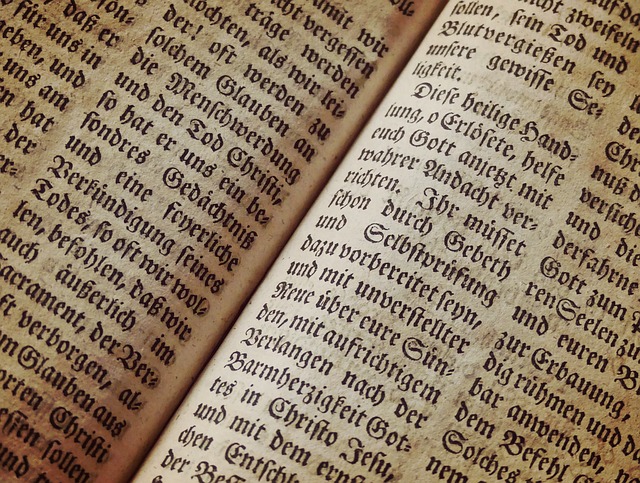
15 règles d’or pour maîtriser la typographie
Dans la construction d’un visuel, le texte est bien souvent indissociable de l’image, même s’il est présent en faible quantité.
Pour des raisons d’équilibre, autant que de puissance de l’image, vous devez consacrer autant de temps à la typographie de ces quelques mots qu’au recadrage et autres effets de filtres retenus.
C’est pourquoi nous vous présentons aujourd’hui 15 règles de typographie à connaître absolument.
1) Connaître les polices de caractère
Chaque police de caractère transmet un message particulier. Une typographie manuscrite n’aura pas le même effet qu’un font plus massif, des mots qui semblent dactylographiés avec une vieille machine à écrire laisseront une impression différente que s’ils paraissent tracés à la craie…
Étudiez les polices, pas seulement pour leur apparence, mais pour ce qu’elles dégagent. Et retenez celles qui correspondront au public et au type de sensation que vous souhaitez communiquer.
2) Limiter le nombre de polices utilisées
La diversité, c’est une très bonne chose. Mais pas pour la conception d’un visuel. Une police de caractère pour le titre, une pour les sous-titres et une troisième pour le contenu, c’est le maximum que vous pouvez vous autoriser.
Ne vous éparpillez pas trop  : les caractères retenus doivent aussi s’associer entre eux.
3) Doser soigneusement la couleur
Méfiez-vous de l’effet arc-en-ciel  : trop de couleurs tuent la couleur. Retenez les couleurs qui ont été sélectionnées pour le visuel et reprenez-les pour les textes.
Ou intégrez dès le départ dans la conception de votre projet la teinte qui sera appliquée aux lignes écrites en respectant toujours cette limite de deux à trois valeurs différentes, au maximum, pour un graphisme.
Soigneur les couleurs pour réussir une typographie
4) Aligner avec précision
Savoir positionner un texte, c’est aussi guider la lecture. Or, dans notre culture, nous avons appris à lire de gauche à droite. Un texte aligné à gauche sera donc nettement plus facile à parcourir.
Respectez le même alignement pour toute la typographie d’un document, sauf à vouloir créer des blocs de texte indépendants les uns des autres.
5) Placer les grands devant, les petits derrière
Quelle que soit la mise en page, l’œil sera en premier attiré par les parties de texte plus grandes, ou d’une couleur différente. Jouez avec les tailles pour capter l’attention des lecteurs.
Il vous faudra sélectionner le mot le plus important, celui qui sera mis en avant. C’est lui qui donnera envie de lire les autres  !
6) Profiter des espaces vides
Le vide, sur un visuel, ce n’est pas le néant, c’est un cadre qui met en valeur ce qui est présenté. Laissez respirer votre texte, ne le collez pas sur les bords de l’image.
Les interlignes, les lignes blanches, sont aussi importants dans la composition de la partie rédigée que le contenu lui-même.
7) Suivre les tendances (ou pas)
Pour trouver l’inspiration, il est bienvenu de regarder ce qui se fait autour de vous et d’en tirer des leçons.
Vous observerez par exemple sur Type Inspire de nombreux exemples de polices ou de mises en page typographiques.
Mais méfiez-vous des modes  : elles peuvent passer très vite et certaines « tendances du jour » seront déjà obsolètes demain. Humez l’air du temps, mais ne cherchez pas absolument à le reproduire s’il ne convient pas à votre projet.
8) Formez-vous
On ne s’invente pas typographe du jour au lendemain. Si vous ne connaissez pas des termes comme « sans serif », ligature ou lettrine, vous n’irez pas très loin dans ce domaine.
Étudiez les différents types de typographie, passez quelques jours à apprendre un mini-glossaire et à voir ce qui se crée de nouveau dans ce domaine ne pourra que vous être utile.
Que vous souhaitiez créer des typographies ou utiliser les existantes, d’ailleurs.
9) Rangez vos typographies en fonction de vos projets
Toutes les sociétés ne communiquent pas de la même manière, ni ne s’adressent aux mêmes personnes. Une police manuscrite sera peut-être plus adaptée pour un public familial que pour les clients d’une banque d’affaires.
Vous pouvez tester plusieurs typographies pour vérifier l’impression qu’elles laissent mais vous gagnerez du temps en réservant les plus fantaisistes aux projets qui le sont aussi.
10) Ne vous éparpillez pas trop
Associer des typographies est un art compliqué. Ce n’est pas pour rien que vous trouverez sur Internet de nombreuses listes de typographies à associer ensemble, y compris sous forme de jeu.
Dans tous les cas, vous constaterez que les polices de caractère présentées vont toujours par deux. Parce qu’au-delà, vous perdrez en lisibilité et en cohérence.